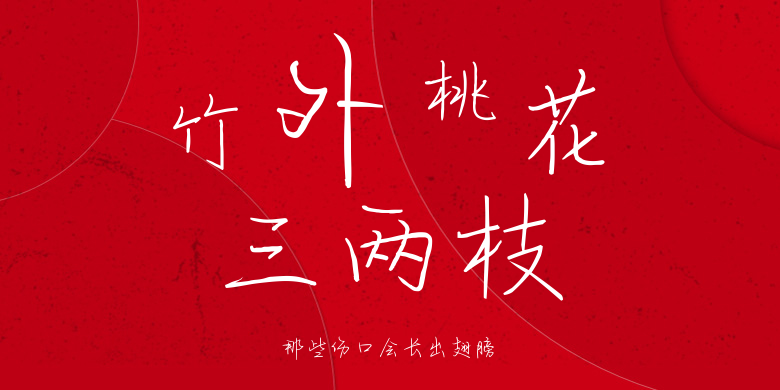
那些伤口会长出翅膀
那些伤口会长出翅膀,这款字体结构工整、笔画清晰,兼顾美观与易读性,适用于标题、正文、海报、包装、LOGO 等多种场景。字形优雅稳定,风格百搭耐看,适配日常排版与创意设计,让文字呈现更舒适、更具质感。那些伤口会长出翅膀一笔一画,皆是细节,以均衡的比例、流畅的线条打造舒适视觉体验,字形端正大气,风格简约现代。无论是商业设计、品牌宣传还是日常排版,都能轻松驾驭,让文字更有格调与力量。那些伤口会长出翅膀字体下载。